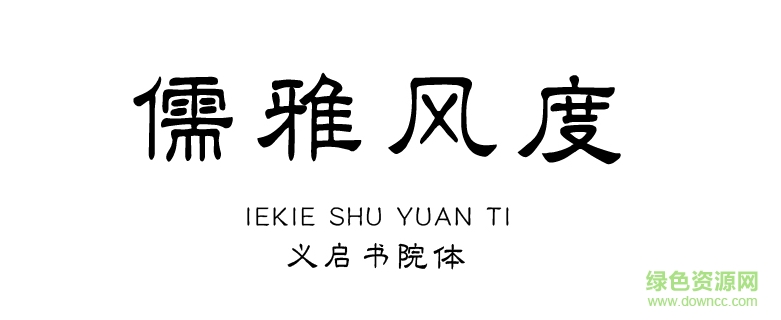
義啟書(shū)院體是一款極具復(fù)古風(fēng)格的的字體,這款字體端莊雅致,非常適用于園林藝術(shù)設(shè)計(jì)方面,喜歡的朋友可以來(lái)綠色資源網(wǎng)下載體驗(yàn)喲!
在古代,人們學(xué)習(xí)的地方叫做書(shū)院,最著名的四大書(shū)院是江西廬山的白鹿洞書(shū)院、湖南長(zhǎng)沙的岳麓書(shū)院、河南登封的嵩陽(yáng)書(shū)院和河南商丘的應(yīng)天府書(shū)院。 如何設(shè)計(jì)出一款具有書(shū)卷氣的字體是義啟字庫(kù)研究的一個(gè)方向。經(jīng)過(guò)對(duì)各種字體的深入研究,義啟字庫(kù)發(fā)現(xiàn)隸書(shū)筆畫(huà)波折起伏,構(gòu)架滄古整體呈扁方形,美觀又規(guī)整易讀,書(shū)卷氣十足。